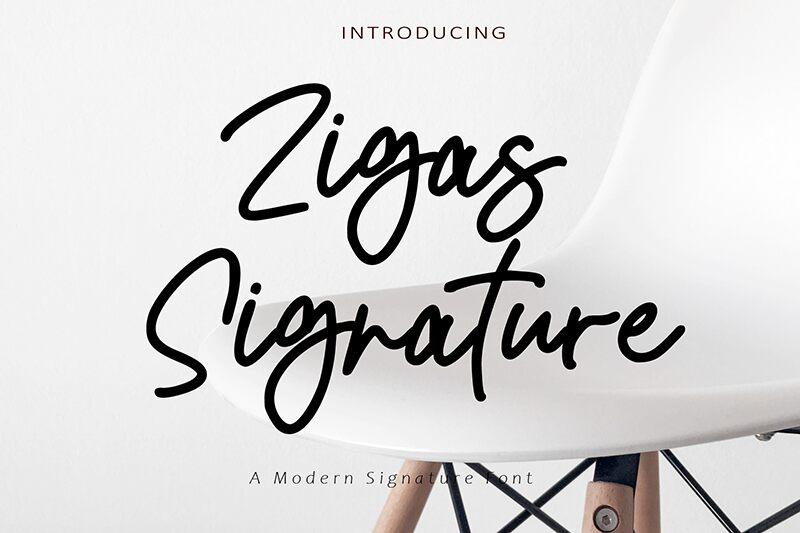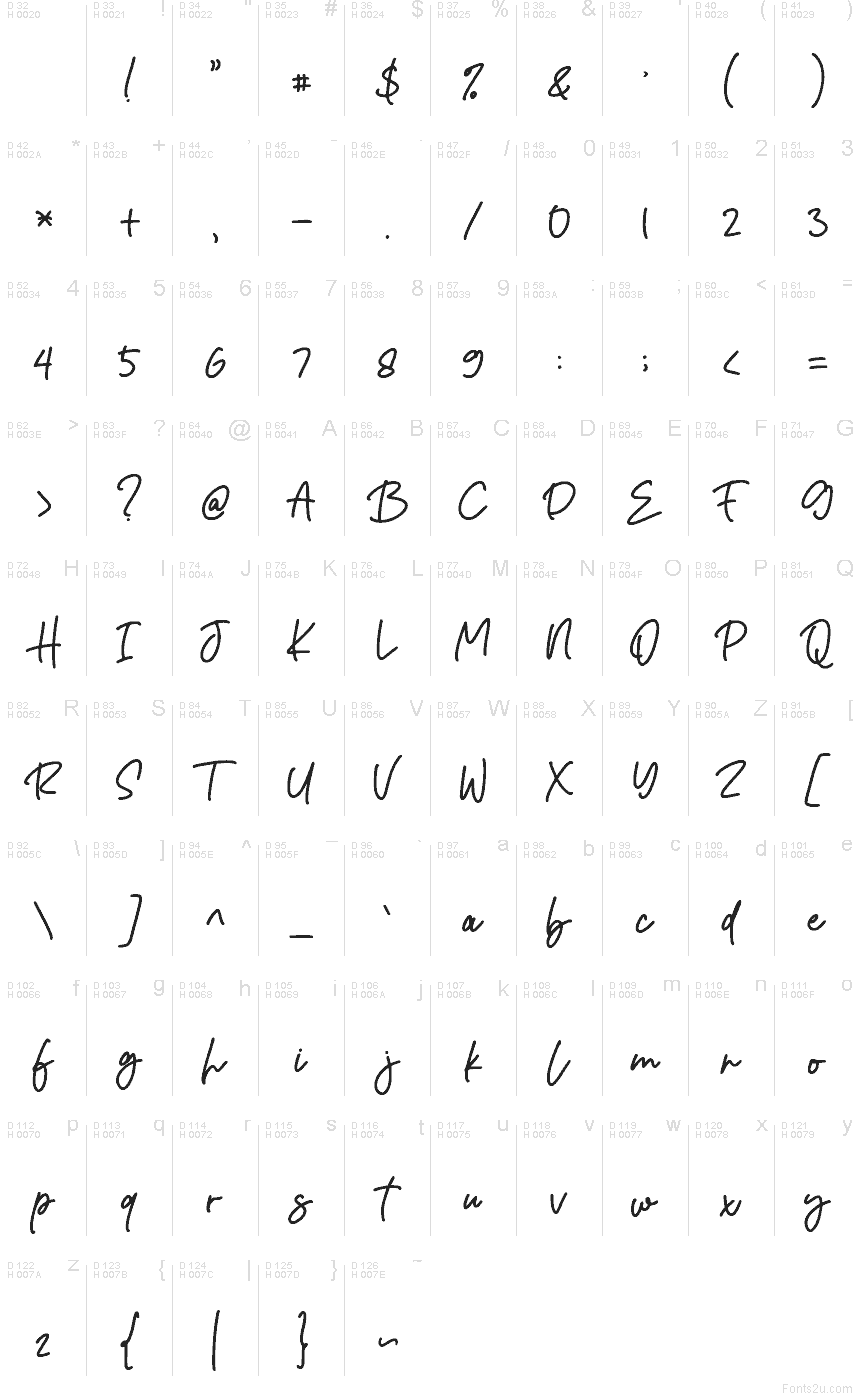
Zigas Signature di Aminmario è un carattere calligrafico gratuito caratterizzato da un tratto sciolto e dallo stile ricercato. Le lettere scorrono in un’unica linea fluida, alternando tratti alti e ariosi a curve morbide, con un ritmo casuale che restituisce l’autenticità di una firma a mano libera, evitando l'eccessiva perfezione digitale.
È ideale per il branding, il packaging di prodotti beauty, header per i social media, menù di caffè, inviti e titoli brevi in cui conta più il tocco personale che la rigidità formale. Essendo un font gratuito, si presta perfettamente a bozzetti di loghi, crediti, targhette e monogrammi, poiché mantiene quel sapore naturale di firma autentica senza scadere nella monotonia di uno script troppo ordinato.